Lettering, calligraphie et typographie : Connaissez-vous les différences ?
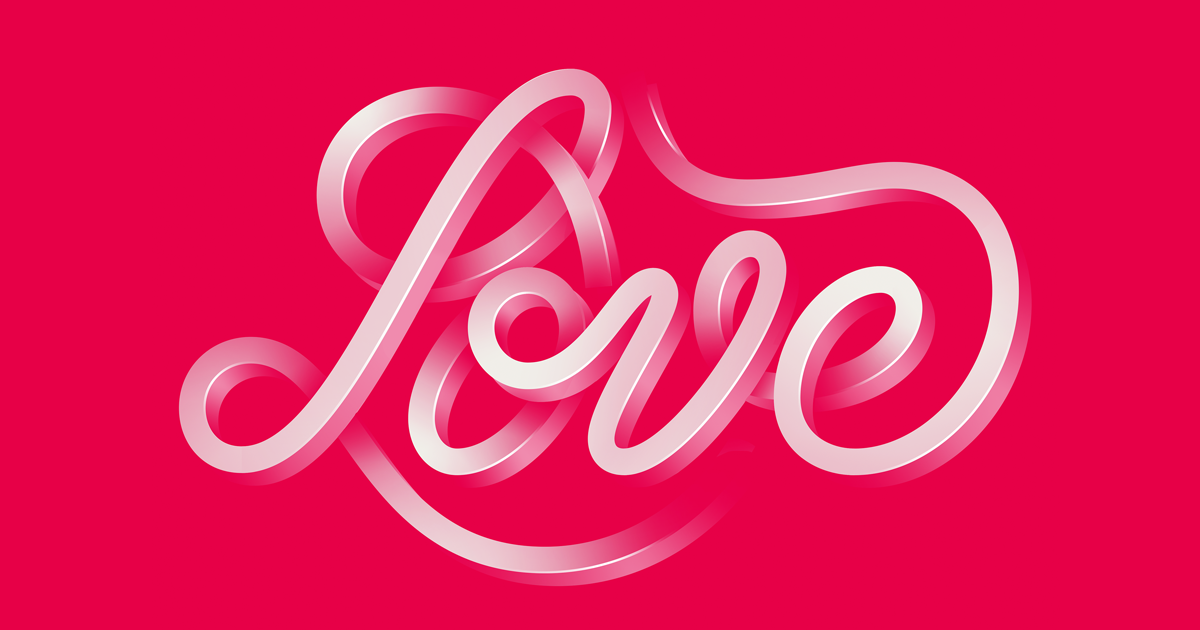
Ces trois concepts font tous référence à des disciplines impliquant des lettres, ce qui est peut-être la seule chose qu'ils ont réellement en commun.
La création de lettres est un monde à part entière, et il n'est pas surprenant que les personnes qui ne sont pas totalement familiarisées avec ce domaine aient quelques doutes. Dans ce billet de blog, nous examinons ce que sont exactement le lettrage, la calligraphie et la typographie, ainsi que les différences entre ces disciplines. Nous décrivons les caractéristiques de chaque discipline et montrons des exemples pour vous aider à les reconnaître. Nous espérons qu'après avoir lu ce billet, vous serez en mesure d'éviter la confusion que ressentent souvent les concepteurs novices, ou ceux qui se spécialisent dans d'autres domaines.
Calligraphie
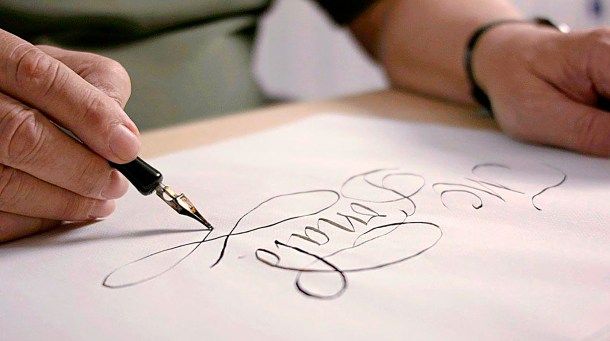
Cette discipline consiste à écrire des lettres en faisant attention à la façon dont les traits ou les éléments qui forment les lettres sont créés, en examinant la vitesse, la direction et la séquence. La calligraphie est toujours réalisée à la main, généralement avec des stylos, des marqueurs ou des pinceaux. Les supports numériques (par exemple, une tablette) peuvent également être utilisés, à condition que la lettre soit dessinée à la main. Chaque partie essentielle d'une lettre doit être créée à l'aide d'un seul trait. Il est interdit de faire des corrections. Cela signifie que chaque lettre est unique. L'auteur d'une calligraphie est la personne qui l'a dessinée.
Le lettering
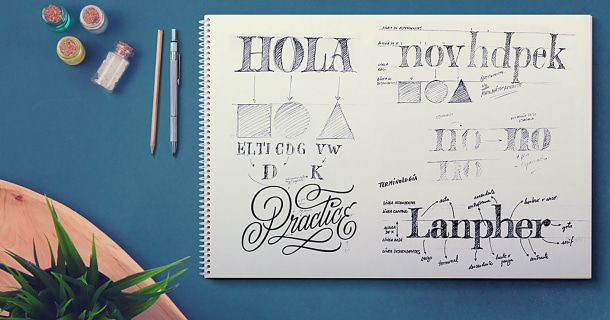
Contrairement à la calligraphie, le lettering consiste à dessiner des lettres ou des mots, et non à les écrire, et l'auteur est autorisé à apporter des corrections. Un autre élément qui différencie le lettrage de la calligraphie est que les lettres peuvent être créées soit à la main, soit à l'aide de vecteurs ou d'autres méthodes numériques. Cela signifie que toutes les lettres ne seront pas nécessairement identiques, mais qu'elles peuvent être copiées pour donner à l'ensemble un aspect plus uniforme. L'auteur d'un projet de lettrage sera la personne qui a dessiné les lettres, ce qui n'est pas le cas lorsqu'il s'agit de typographie.
Typographie
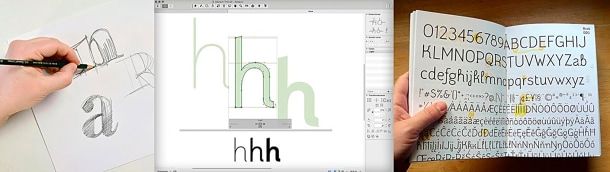
Les créateurs de caractères ne créent pas de lettres ou de glyphes uniques comme les calligraphes, et ne dessinent pas de mots comme les artistes du lettrage. Une police de caractères est un ensemble unique de caractères qui sont unis par des choix stylistiques. Le créateur de caractères ne se contente pas de concevoir les lettres, il les programme également et établit une série de paramètres clés qui sont systématiquement répétés sur l'ensemble des caractères.